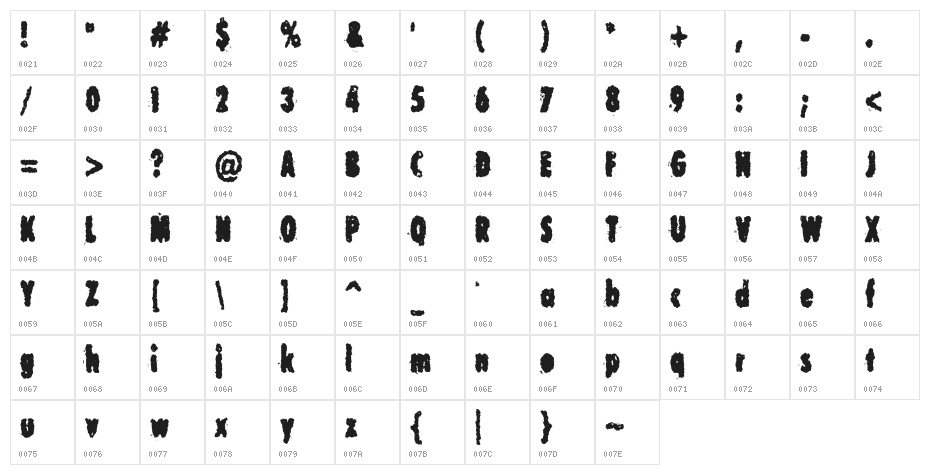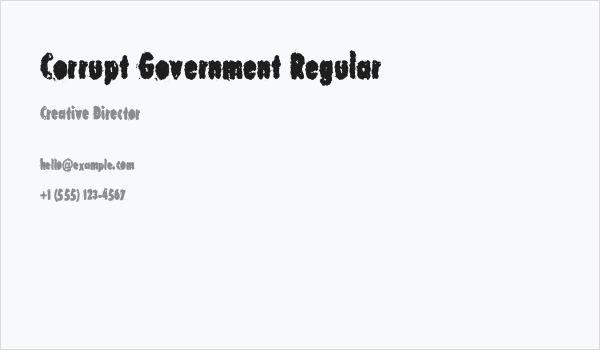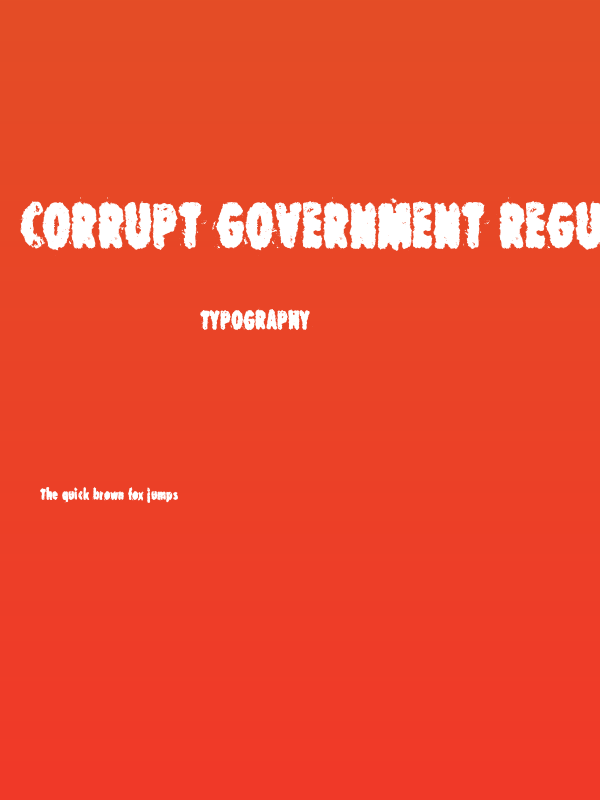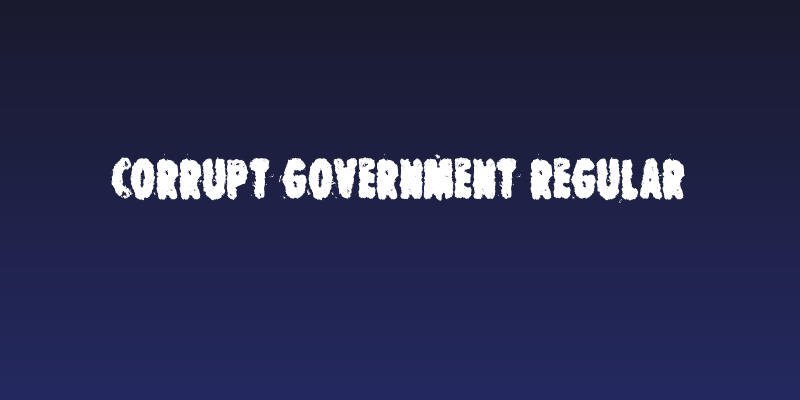
Corrupt Government Regular Font
✎ Distorted Eroded
| Categorie | Distorted Eroded |
| Stile generale | Grunge, Edgy, Rebellious |
| Caso d'uso | Headlines, Posters, Artistic Designs |
| Progetti proposti | Ideal for album covers, posters, street art designs, and any project needing a bold, edgy aesthetic. |